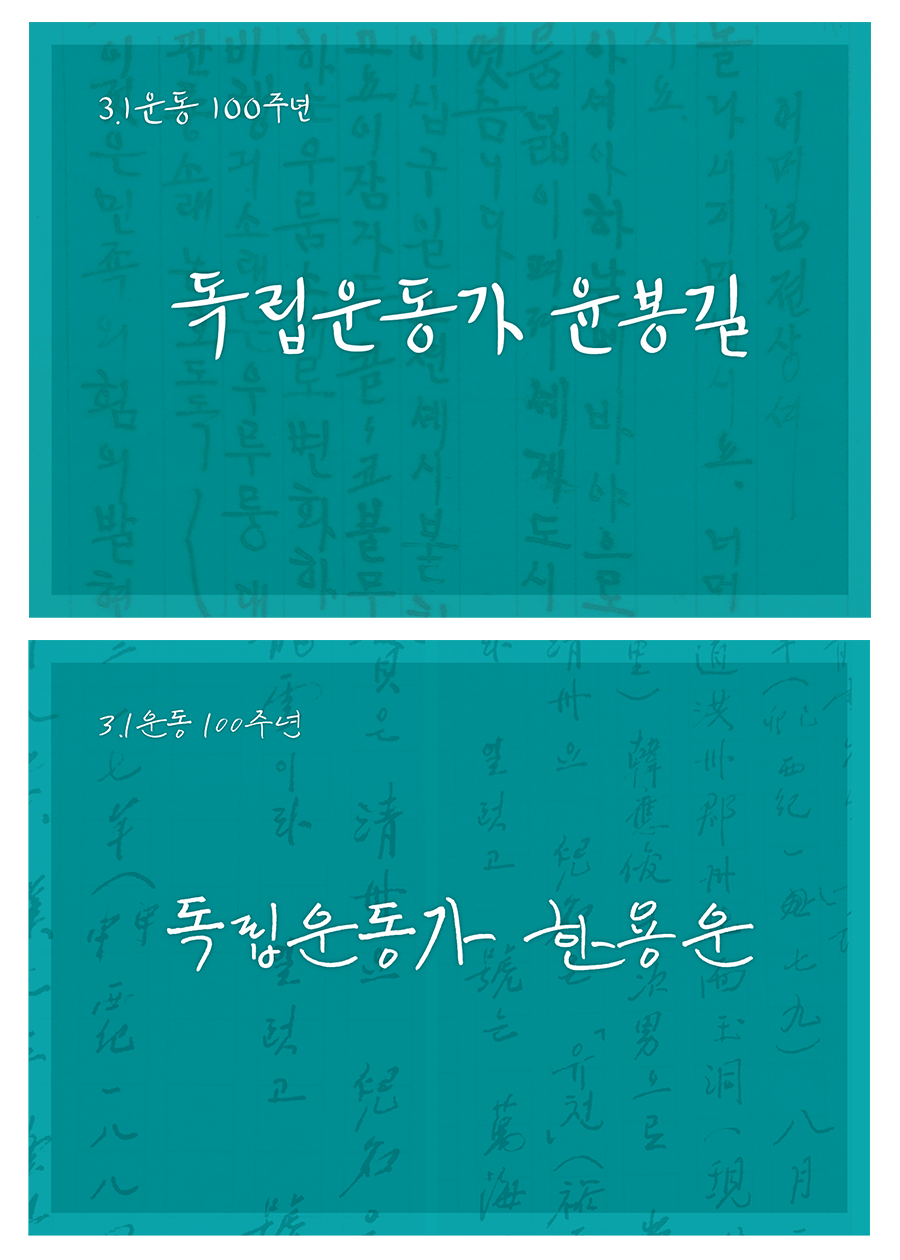
GS칼텍스, 독립운동가의 손글씨를 바탕으로 폰트 개발
GS칼텍스가 3·1 운동 100주년을 맞이하여 독립운동가 윤봉길과 한용운의 서체를 개발했다. 각 폰트의 이름은 ‘독립서체 윤봉길’과 ‘독립서체 한용운’이다.
GS칼텍스는 일제 치하에서 조국의 독립을 위해 몸바쳤던 선열들의 발자취를 따라 일부 기록으로만 남아있는 독립운동가들의 실제 글씨체를 연구하여 현대적으로 재해석해 친필과 유사하게 복원·제작했다. 매헌 윤봉길은 일왕의 생일 행사장에서 거사를 일으켜 조국 독립운동에 중요한 방점을 찍었으며, 만해 한용운은 ‘님의 침묵’을 출판해 저항문학에 앞장서고, 민족대표 33인 중 한 명으로 3·1 독립선언을 이끈 인물로 두 순국선열의 손글씨가 디지털 폰트로 재현되었다는 것 자체만으로도 큰 의미를 지닌다.